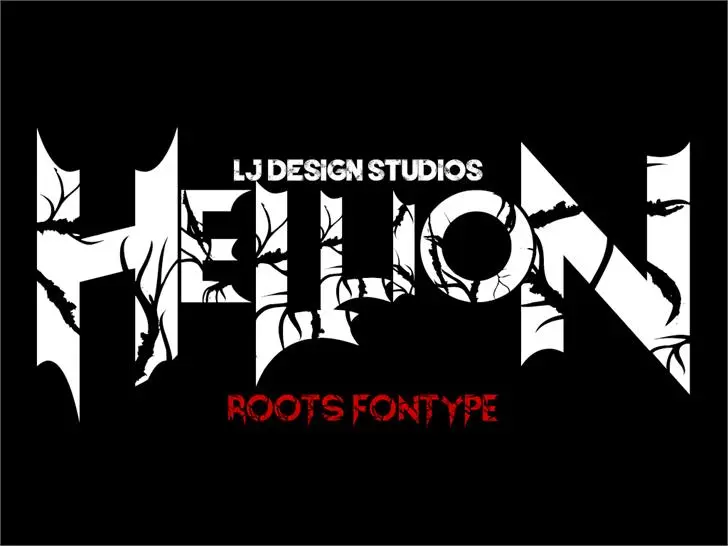
Hellion font
A Hellion é uma fonte ornamental com traços elegantes e fluidos que se destaca por sua versatilidade na criação de designs decorativos. Seu designer, Hamilton, criou uma peça de arte tipográfica que combina delicadeza e forte característica em cada letra. Esta fonte é perfeita para quem procura um estilo único e sofisticado para textos importantes ou aplicações gráficas. Para acesso ao uso comercial, visite o site especificamente indicado na descrição original. A Hellion oferece uma paleta de opções que permite criar designs inovadores e imprimíveis com facilidade.